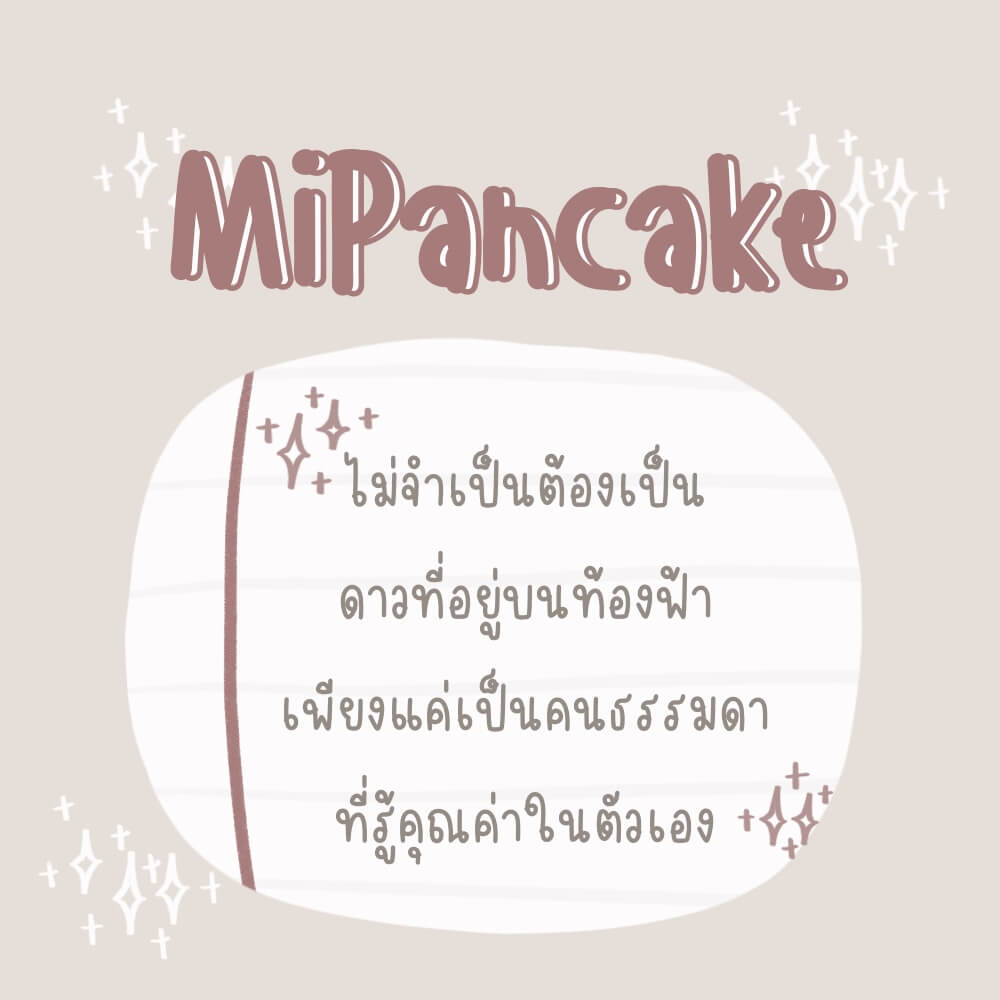
มาแล้ว! ฟอนต์ไทยสไตล์น่ารัก สดใส เอาใจเด็กวัยรุ่นและวัยเรียน ที่อยากจะมีฟอนต์น่ารัก ๆ ไว้ทำงานนำเสนอ งานอาร์ตเวิร์ต ตกแต่งโน้ตให้สวยน่ารัก ๆ ทีมงานได้รวบรวมฟอนต์ไทยใหม่ ๆ จากเว็บไซต์ ฟอนต์.คอม มาแนะนำให้ดาวน์โหลดกันค่ะ
แจก 8 ฟอนต์ไทย สไตล์น่ารัก เอาใจวัยเรียน สำหรับตกแต่งงานนำเสนอ
ฟอนต์ที่นำมาแนะนำกันวันนี้จะเป็นฟอนต์สไตล์น่ารัก ๆ เหมาะกับนักเรียน นักศึกษา หรือคนทำงานที่ชอบตกแต่งงานสไตล์หวาน ๆ น่ารัก หากสนใจนำไปใช้ด้านการศึกษา การทำงานส่วนตัวที่ไม่เกี่ยวข้องกับเชิงพาณิชย์ก็สามารถเลือกดาวน์โหลดกันได้เลยนะคะ
1. เอฟซี เครยอน (FC Crayon)
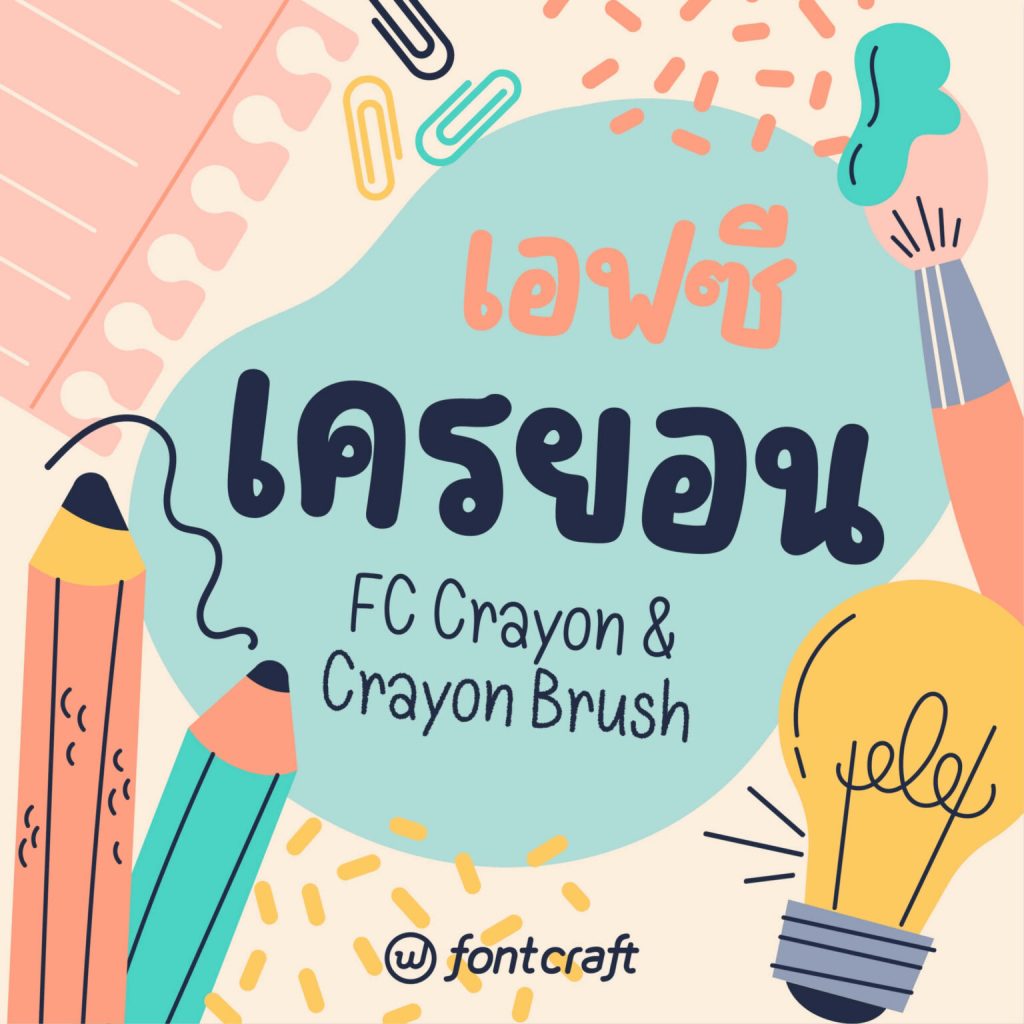
2. บิสกิต (Biscuit)
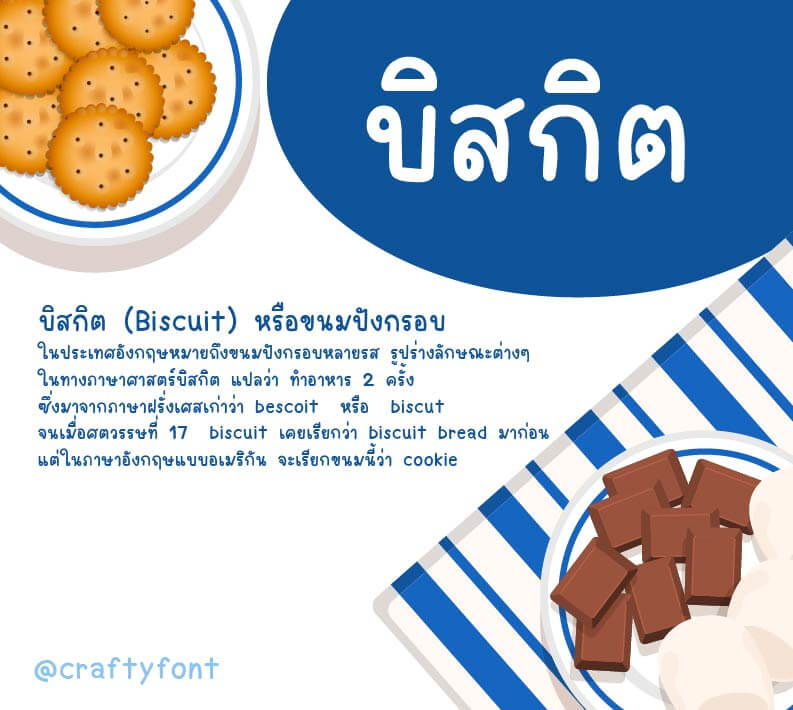
3. tintin ver-2
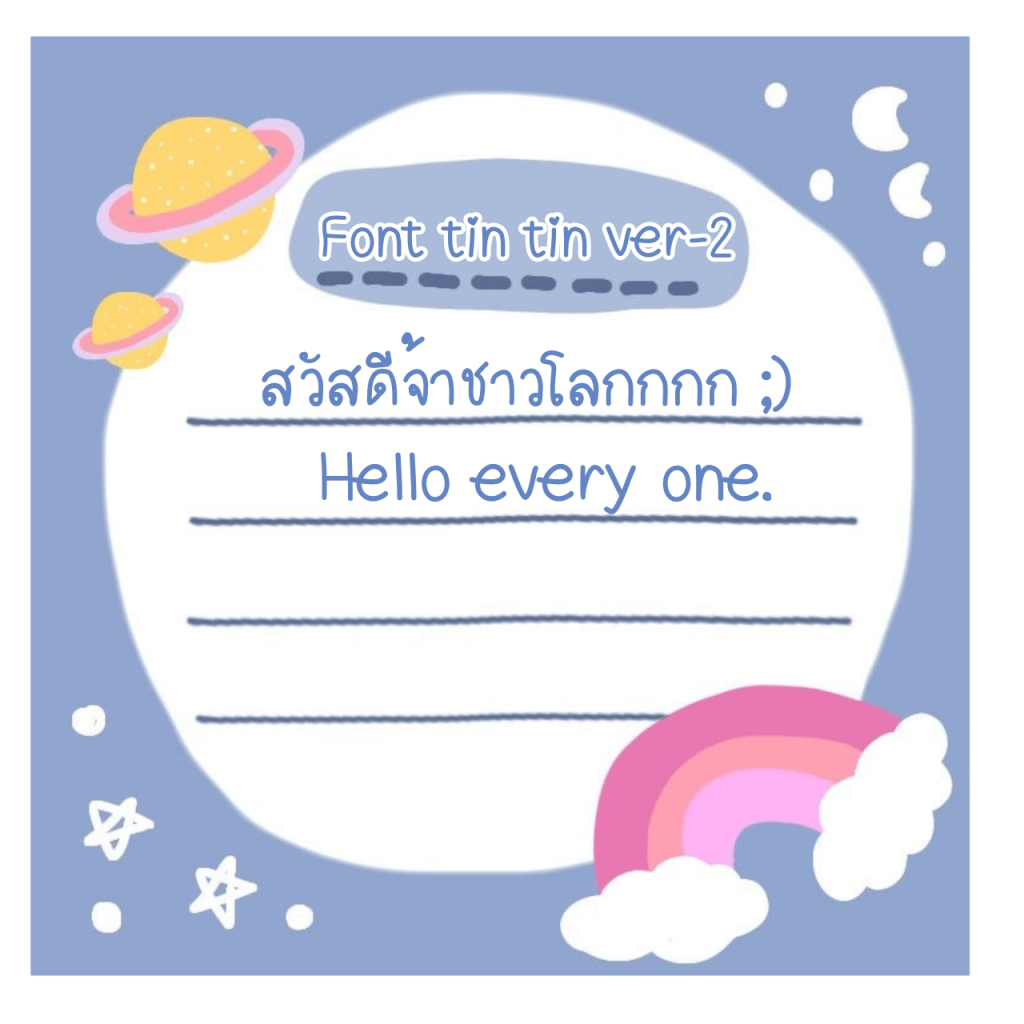
4. MiDaifuku
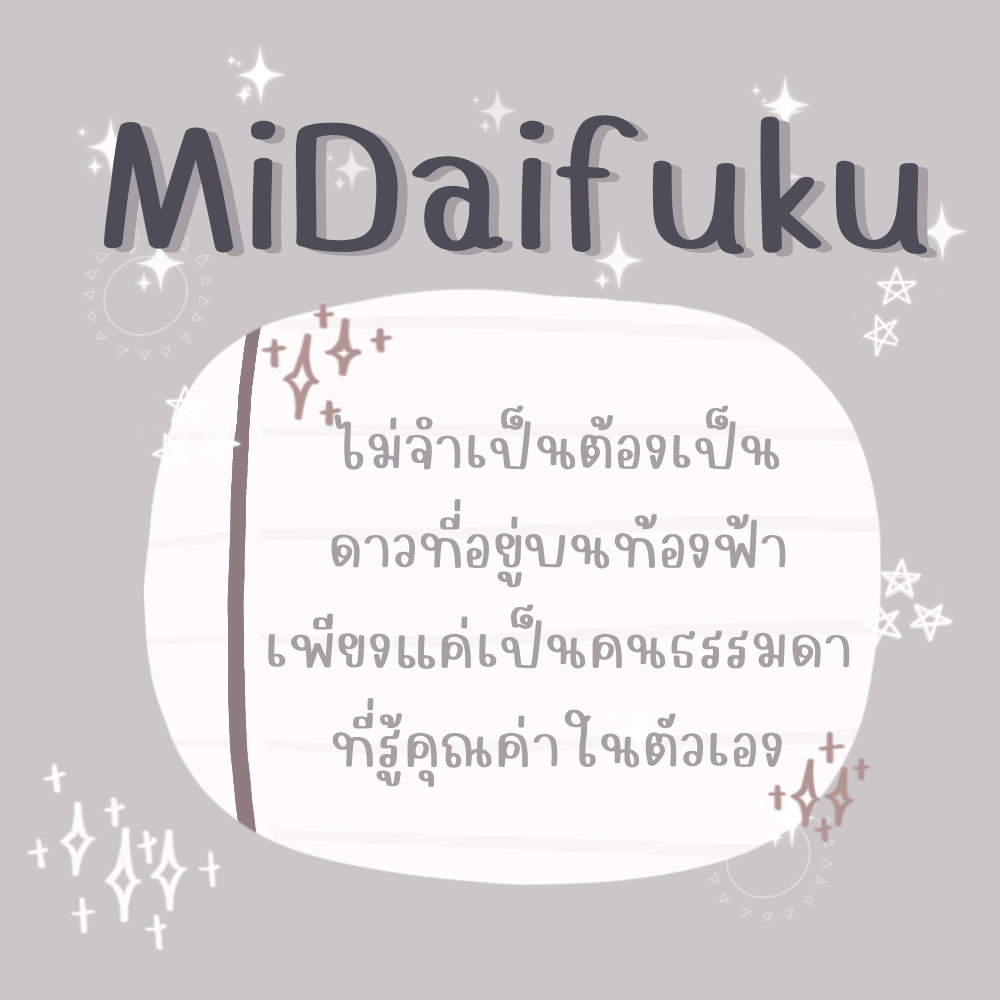
5. ไอติม (ice cream)
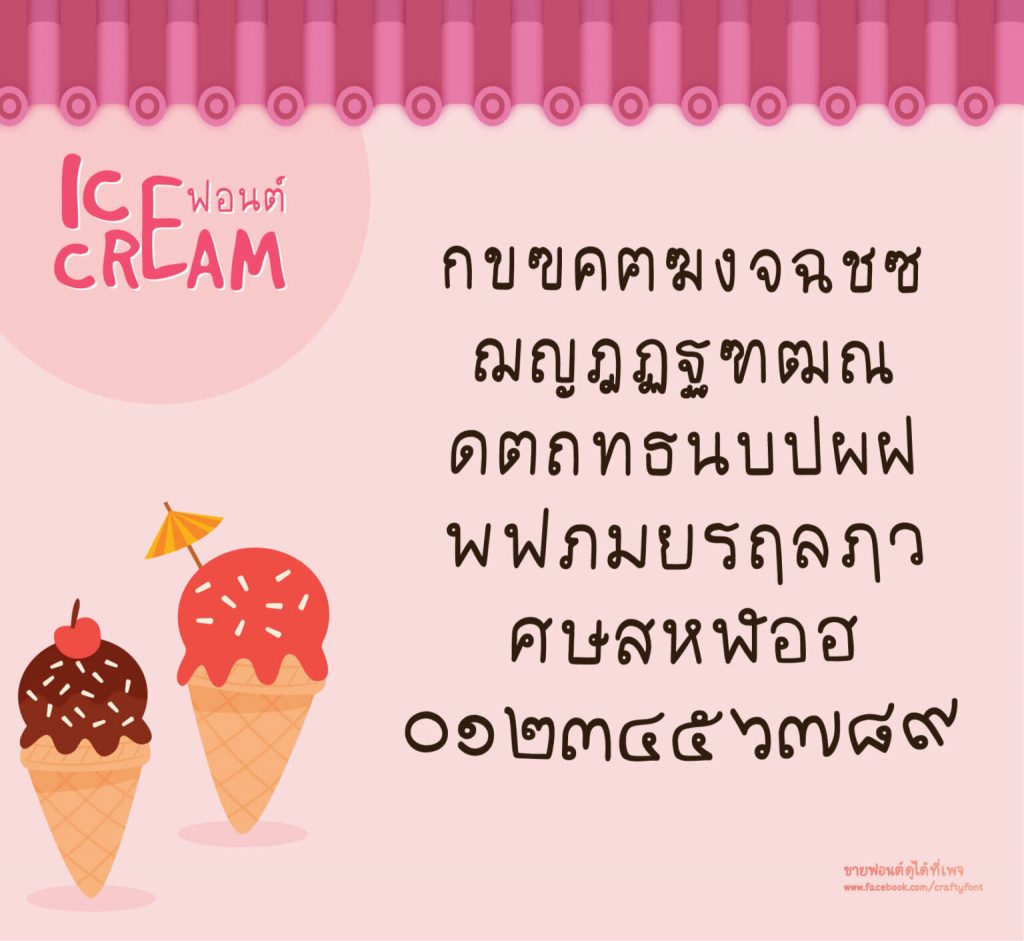
6. ช็อคโกแลตที่หายไป (Chocolateteehaypai)
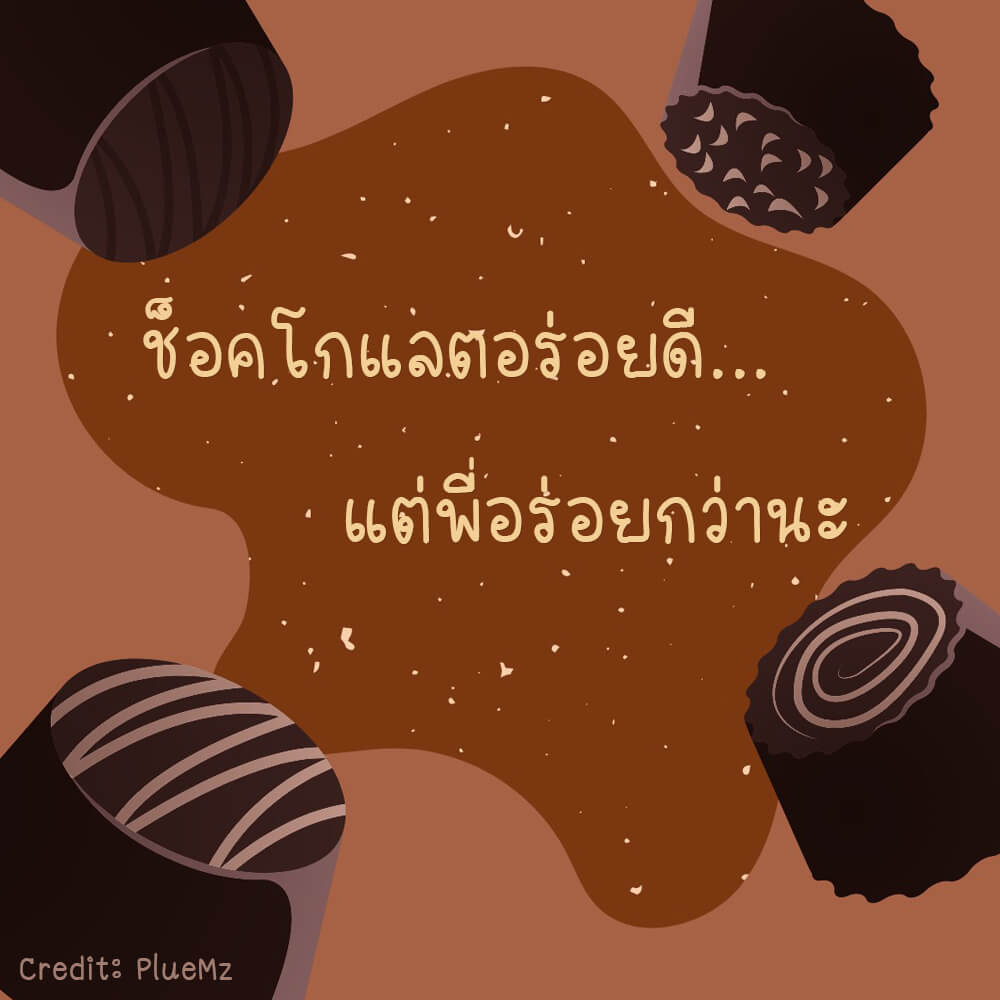
7. Doughnut
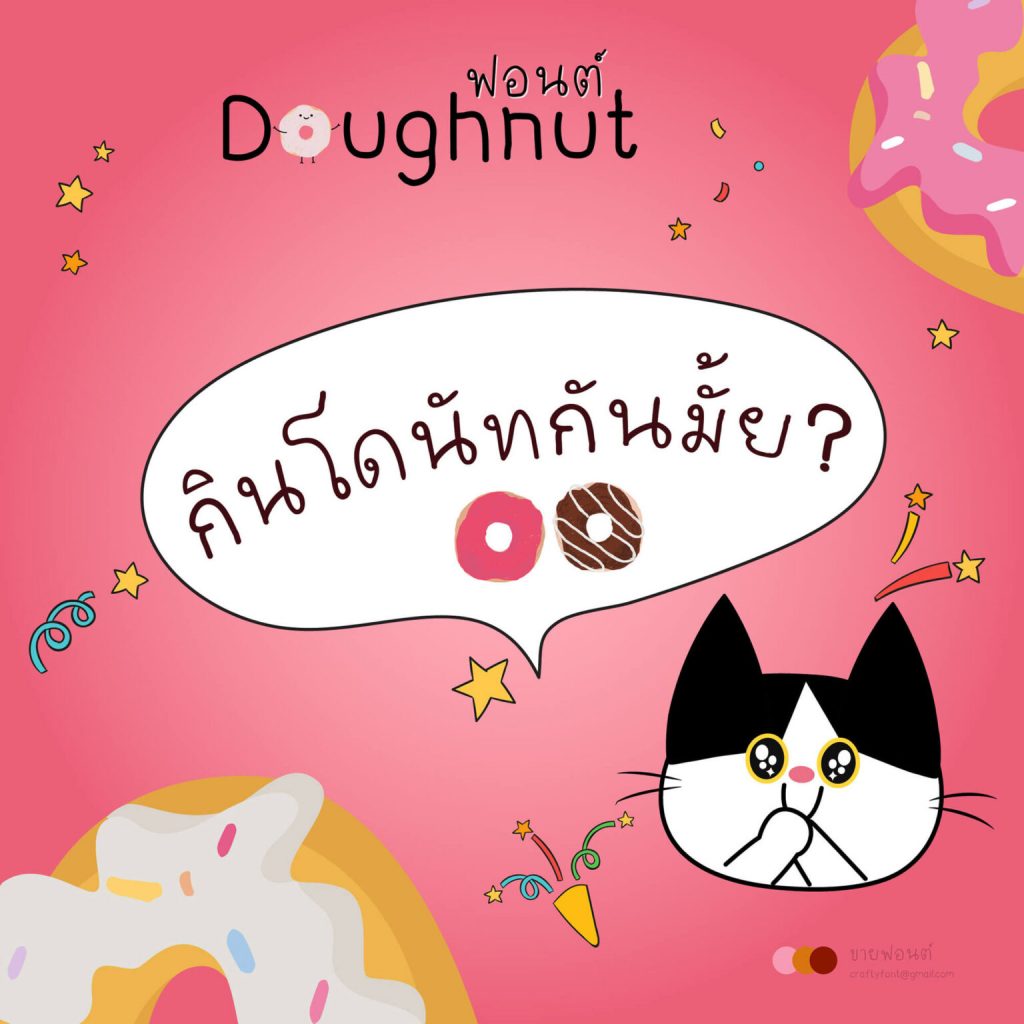
8. MiPancake